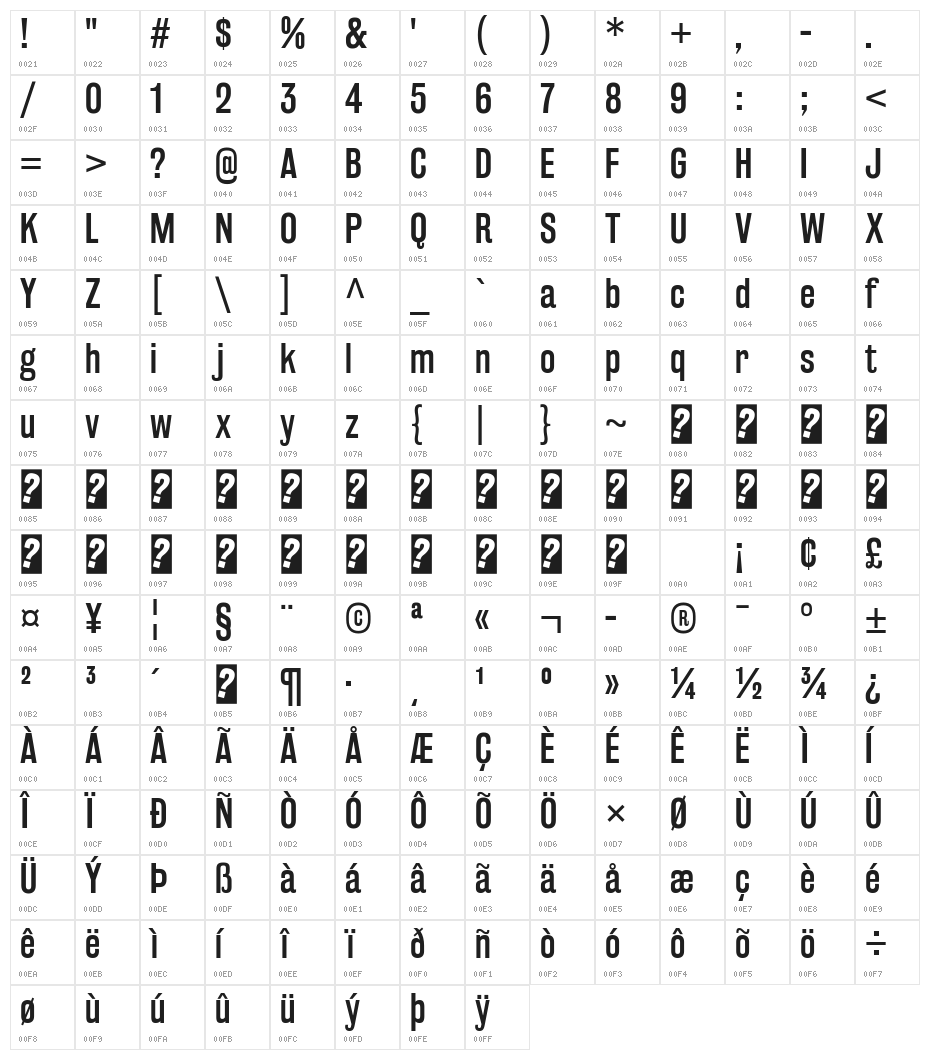
RakeslyRg-Regular Font
✎ Sans Serif
| 使用场景 | Headlines, Logos, Branding |
| 推荐项目 | Ideal for branding, advertising, headlines, and digital media where a modern and bold statement is needed. |